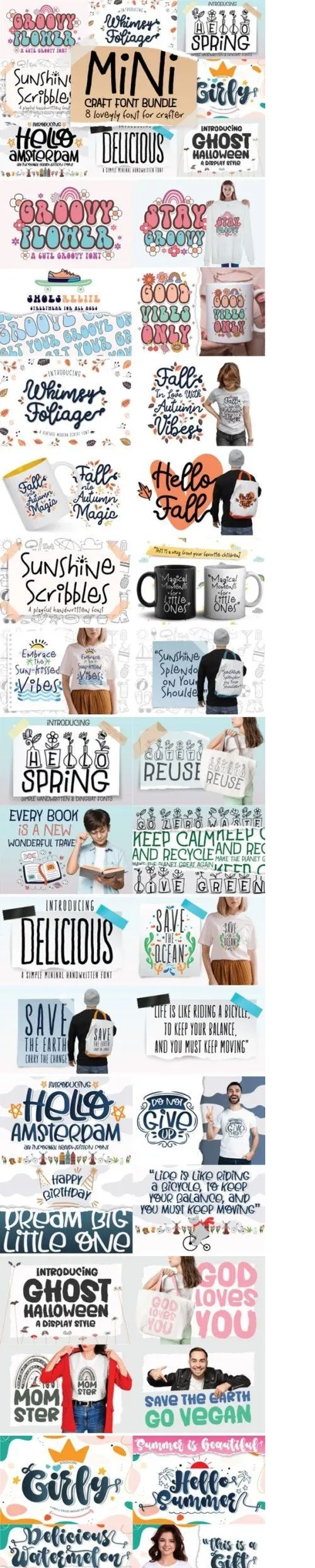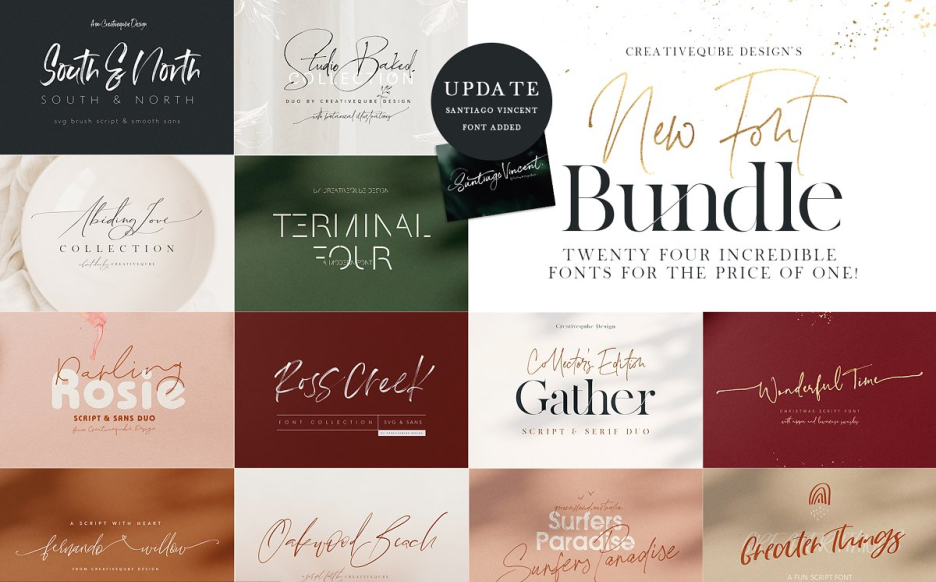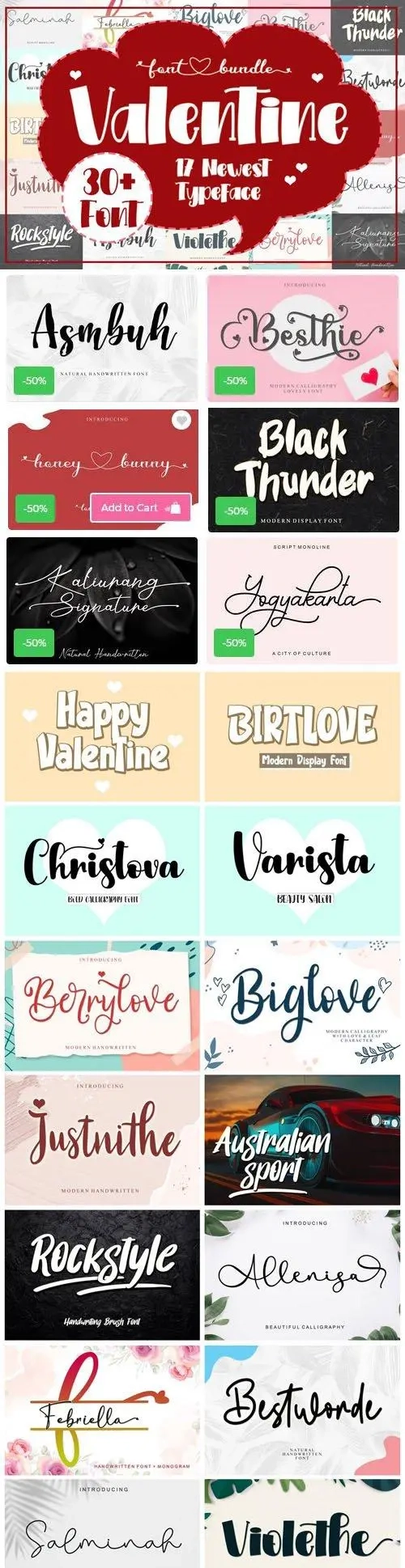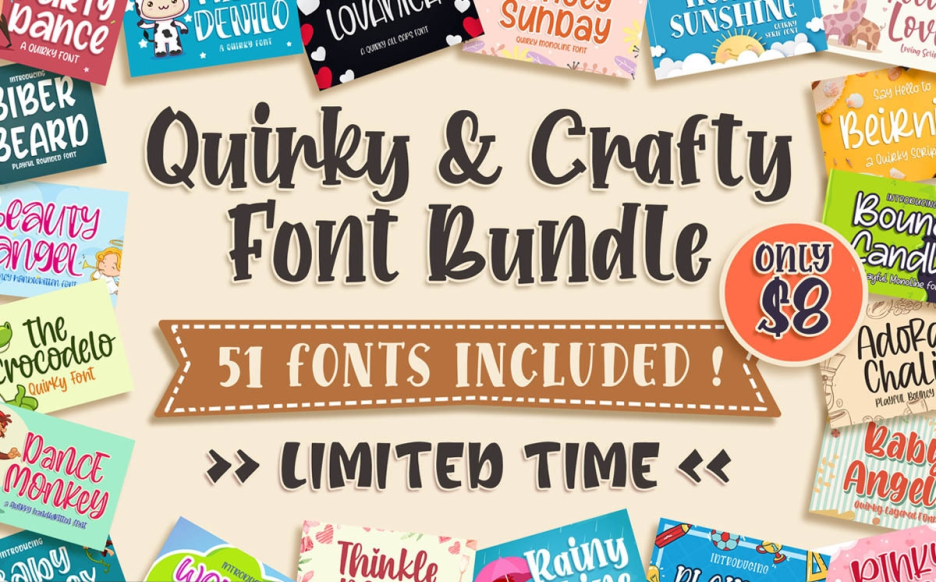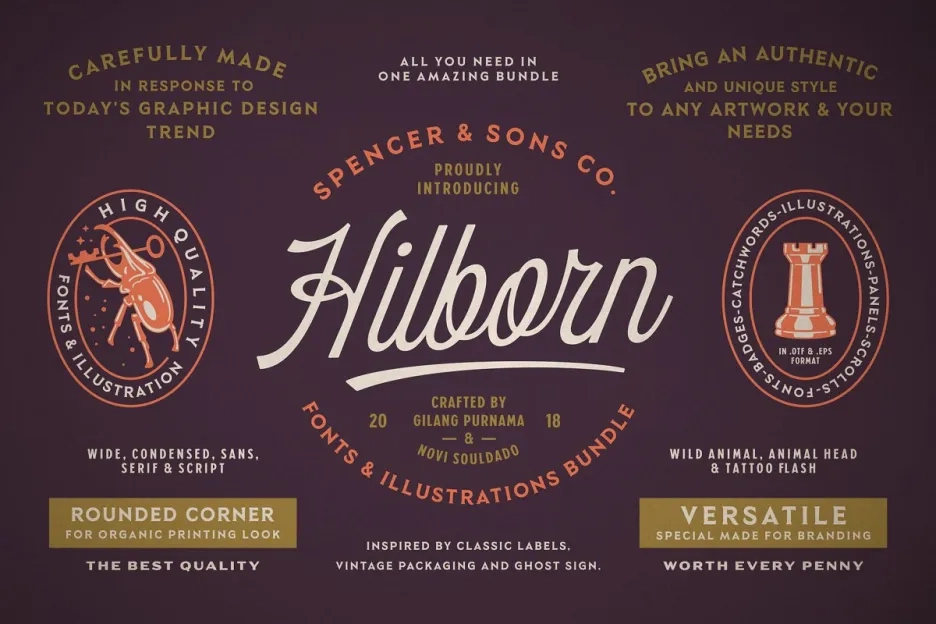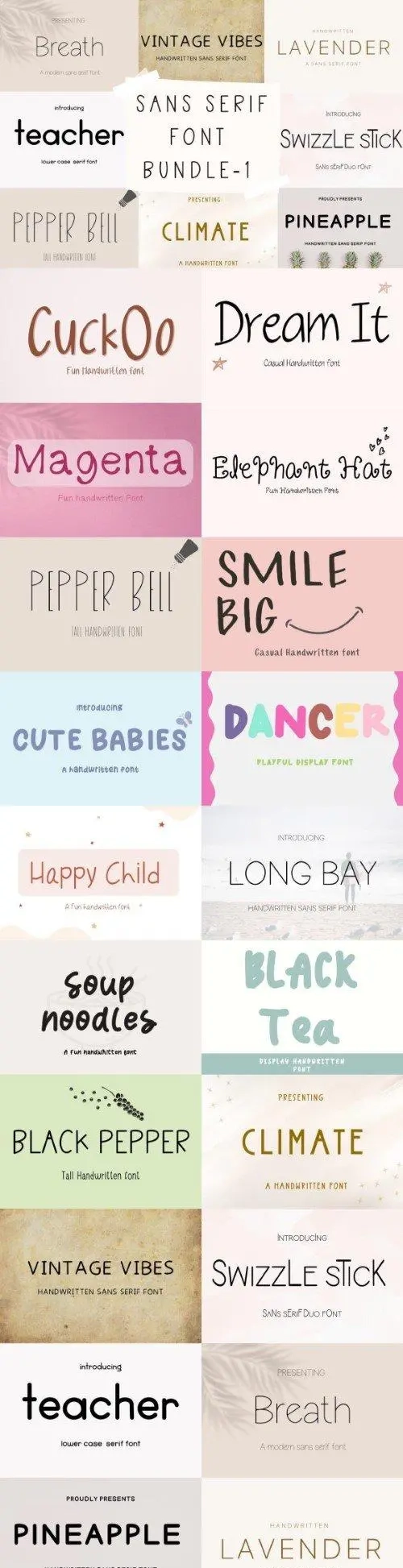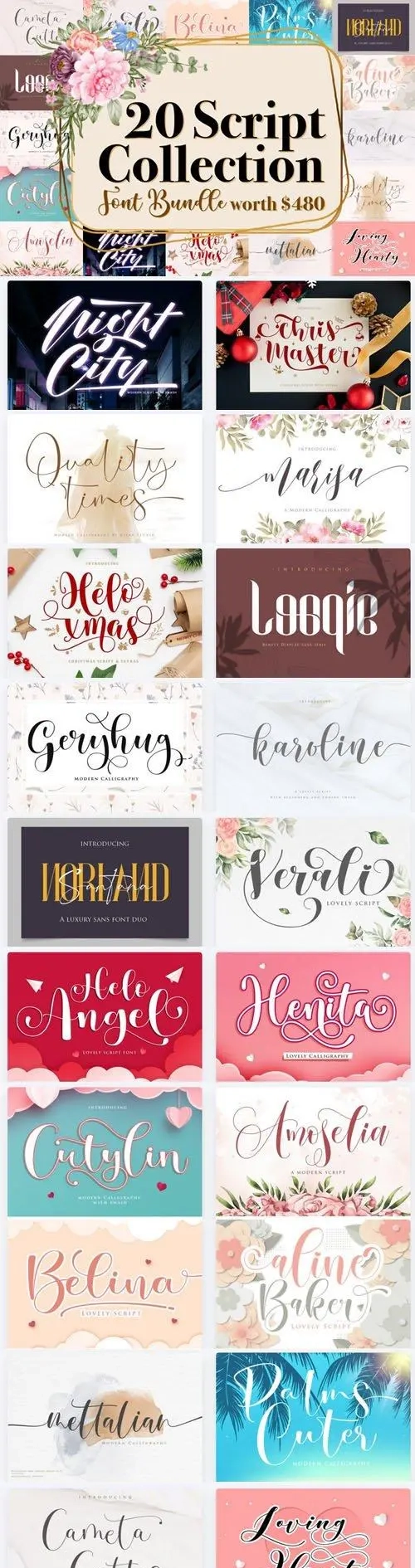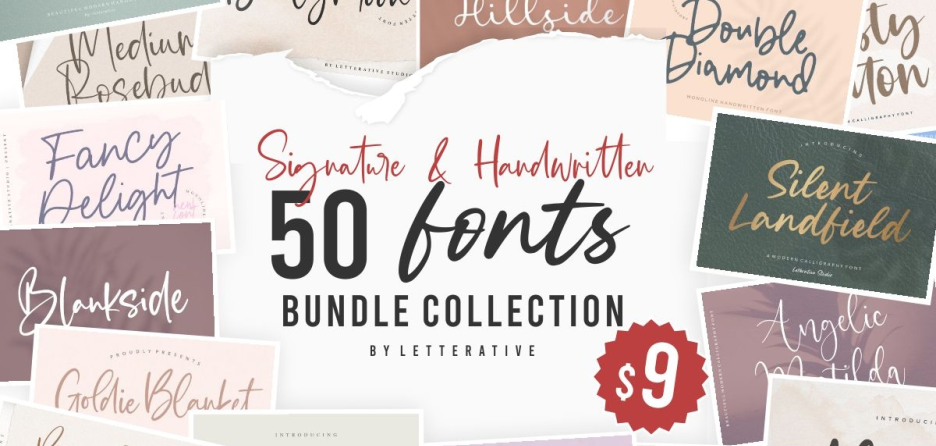
嘿,充满创意的你!🎨✨准备好为你的设计工具箱加速了吗?我们整理了Brushespack的第157部分精选内容,相信我,这绝对是一座字体排印的宝库。从俏皮的手写体到稳重的衬线体,这20个超棒的字体系列是你让任何项目脱颖而出的黄金门票!🚀
为什么要使用这些字体系列?
因为你的字体不该枯燥无味!😴❌这些字体系列充满个性,让你瞬间拥有多样选择——从手写风格的魅力到时尚专业的质感。无论你是在设计LOGO、邀请函,还是社交媒体创意素材,找到合适的字体就像为菜肴加入完美的调味料。🌟我们开始吧!👇
精选20款字体组合推荐
特制手写字体包 – 50款字体
五十款惊艳手写字体捆绑销售?算我一个!🖋️✨ 这套合集充满个性——完美适合婚礼请柬、品牌设计,或为您下一件杰作增添一抹优雅韵味。手写字体爱好者的天堂!🌸
时光与地点字体包 – 23款字体
衬线、无衬线及展示字体的精美融合,尽显永恒韵味。🕰️🌍 这款字体包是您需要兼具格调与多样性的项目首选。每一款字体都在诉说一个故事!📖
手写字体合集包 – 20款字体
二十款精心打造的手写字体,绝对是视觉盛宴!🍭✨ 从优雅的旋涡线条到现代风格,这套字体在标志、引文和时尚设计中效果惊人。相信我,你的客户一定会为之倾倒!😍
签名与手写字体套装
没有什么能比得上那种个性化、手写质感的触感!✍️💖 这款字体包汇集了正宗的签名与手写风格,散发着真实的魅力。非常适合品牌设计、包装,或为您的数字作品增添人文气息。🎯
无衬线手写字体包
现代、简洁,又超级亲切!🖤✨ 这套字体集完美融合了手写风格的美感与无衬线字体的流畅感。多种字重让你在保持手绘温馨感的同时拥有更多灵活选择。简直太棒了!🏆
精美字体套系合集
一个精心策划的万能宝库!🎉 从手写体到衬线体,这个合集应有尽有。就像拥有一把字体界的瑞士军刀——无论项目大小,随时待命。华丽、多变,绝对激发灵感!🌈
手写字体合集 – 20款高级字体捆绑包
优雅、现代又充满趣味——这份字体系列涵盖了所有手写风格!🎭✍️ 无论你在设计高端品牌还是有趣的派对邀请函,这20款优质字体都能带来惊艳效果。品质出众,格调满分!🌟
浪漫字体合集包
爱意弥漫在空气中,也流淌在字里行间!💘🌹 本字体包包含令人心醉的手写体、衬线体与展示字体,完美适用于情人节项目、婚礼套装,或任何需要增添浪漫与魅力的设计。💌
S&S Hilborn 字体包
一款多功能的强大无衬线、衬线和展示字体,从细体到特粗体!💪📐 这款字体包是数字和印刷设计的理想之选。简洁、醒目且极其可靠。🔥
手写字体包 – 20款精选字体
又是一套出色的手写字体阵容!🖋️🎉 每款字体都是一件艺术品,拥有优美的字重和风格,为任何项目增添优雅气质。从徽标到请柬,这款字体包都能满足你的需求。准备好提升你的排版水平吧!🚀
专业合集字体包
精致、百搭,且极具专业感!👔✨ 这套字体系列融合了优雅衬线体与现代无衬线体,还加入了手写体和展示字体,恰到好处。非常适合企业品牌设计、演示文稿以及需要彰显格调的高端设计项目。💼
古怪手作字体系列
释放你俏皮的一面!🎨🤪 这套字体包充满了有趣、奇特的字型——俏皮的手写体、醒目的展示体和迷人的衬线体。非常适合手工艺项目、儿童读物,或任何需要增添欢乐氛围的场合。🌟
节日礼包 – 69款高级字体 & 6款高级图形
这可是超级大优惠!🎄🎉 69款字体加6款高级图形?必须拿下!这款合集包含从优雅手写体到醒目展示体的各类字体,非常适合节日贺卡、应景品牌设计,或任何季节性项目。吼吼吼,这是一场字体的盛宴!🎅
新款潮流字体合集 + 附赠品
保持潮流领先,尽在这款时尚收藏!🚀🔥 从现代衬线字体到粗体无衬线字体,处处散发着清新、当代的气息。此外,你还将获得额外赠品,让这款组合包物超所值。你的设计将成为全城热议的话题!💬
高级字体组合包
只选最好的!🥇✨ 这款高级字体包精选多样风格与字重的优质字体。从细体到粗体,这些字体营造出优美的层次感和深度。任何严肃设计师的必备之选。👩🎨
海量字体包
它规模庞大,我们指的是超级庞大!🏔️📦 此套装提供从优雅到现代的丰富字体库。无论面对何种设计挑战,您都不会缺选项。仿佛一个字体宇宙尽在您的指尖。🌌
Creativeqube 新款字体套装
清新、多变,随时准备引爆创意!🎸✨ 这套由Creativeqube推出的字体包精心融合了多种风格与字重。OTF和TTF格式让您在任何平台上都能轻松使用。为您的创意武器库再添利器!💪
Mini Craft Bundle Font
小巧但强大!🧵🖤 这套多功能字体包非常适合手工制作、品牌设计等场景。简洁的线条和俏皮的字符让使用过程充满乐趣。易于阅读且富有魅力——你的手工项目一定会爱不释手!🎨
最新情人节字体包
用这套浪漫字体合集传播爱意吧!💕🌹 涵盖手写体、衬线体和展示字体,专为情人节、纪念日或任何需要真情实感的项目量身打造。完美适用于贺卡、社交媒体帖子和品牌设计!💌
十月特惠字体合集
为你的字体收藏带来一份特别惊喜!🍂🎃 这套字体合集包含衬线体、无衬线体、手写体和展示字体,非常适合秋季项目、万圣节主题或任何需要独特风格的设计。抓住这个限时宝藏吧!🕸️
总结
以上就是20套超棒的字体合集,能够激发你的创意并提升你的设计水平!🚀✨ 无论你喜欢优雅的手写体、独特的工艺字体还是专业强大的字体,Brushespack 的第157期合集都能为每个人带来惊喜。别再犹豫——你的下一部杰作只需点击一下即可获取!🎨💖